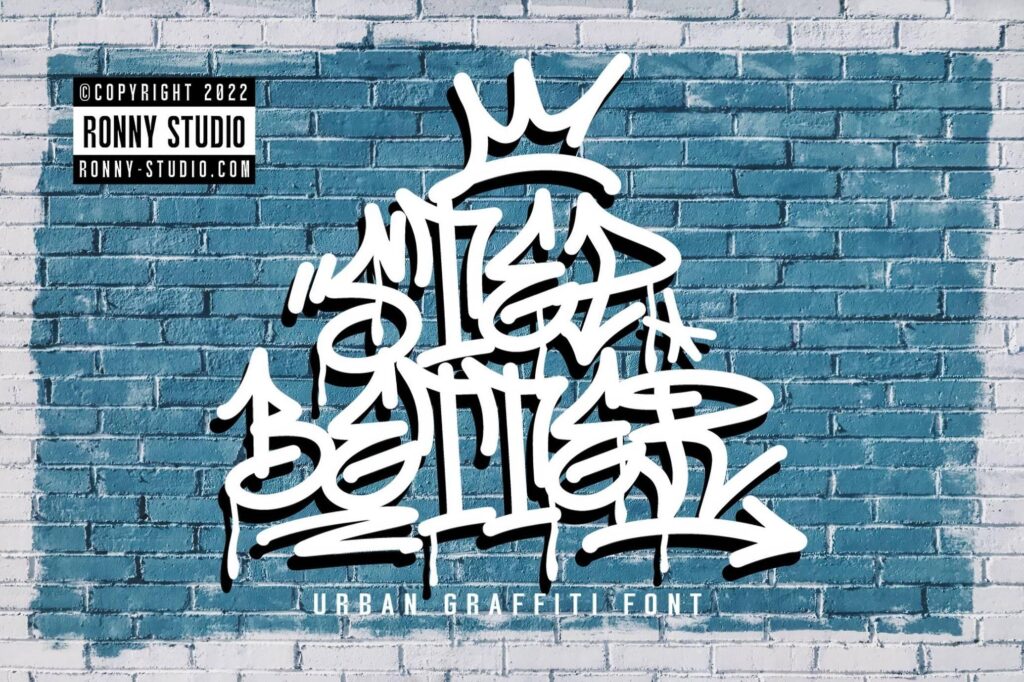
本記事では、用途がかなり限定されそうな超個性派の英語フリーフォントを紹介します。
使いやすい定番系フォントもうれしいですが「これどこで使うの?」と使う場所が限られそうな超個性派フォントも、無料ならアリ!ですよね。
それでは、早速みていきましょう。
クセがスゴい!用途が限定されるけどインパクト大!ユニークな英語フリーフォント【商用利用可能】
The Free Funky Fonts Bundle
Step Better — Urban Graffiti Tags Font
Lorida — Condensed Display
TGHEAD GEOMETRIC FONT
EVA POSHY FONT
TURKEYES — BOHEMIAN TYPE
WOLFGANG KRAUSS — MODERN FRAKTUR TYPE
Fleuron – Free Floral Display Font
Chubbo – Free Display Font
Hofmann – Free Experimental Typeface
Cibiru – Free Display Font
Gawker – Free Display Typeface
SURREAL PSYCHEDELIC TYPEFACE
▼商用利用可能なストリートの落書き風フォント「Kelsi – Free Graffiti Style Bubble Font」。ポップな雰囲気が気軽に演出できます。
Kelsi – Free Graffiti Style Bubble Font
▼商用利用可能なSVGフォント「LYON & CREST SVG FONT」。フォントのかすれ具合を強調したいなら、写真やイラストの上に重ねるのがオススメ。
LYON & CREST SVG FONT
▼商用利用可能なディスプレイフォント「KILLVINERS BLACKLETTER FONT」。クラシックな雰囲気もありつつ、今風のストリート感のある媒体にも対応できるタイムレスなフォントです。
KILLVINERS BLACKLETTER FONT
▼どこかレトロな雰囲気も感じさせるデザインフォントLEONE。
LEONE – FREE MODERN WESTERN FONT
▼大文字(縦長)と小文字(横長)を組み合わせるとスポーツチームのロゴっぽくなるフォントVINTAGE MONOGRAM FONT。
VINTAGE MONOGRAM FONT
▼アフリカの部族が使う文字や象形文字のようなJELANI DISPLAY FONT。
JELANI DISPLAY FONT
▼あえて混ぜて使いたい、5種類のフォントスタイルとボーナススタイルを収録したEXTRA CHEESE FONT COLLECTION。
EXTRA CHEESE FONT COLLECTION
▼斜めにカットしたようなズレを表現したフォントBISECT DISPLAY FONT。
BISECT DISPLAY FONT
▼中世ヨーロッパの物語のタイトルに使われていそうなAVIORTE BLACKLETTER FONT。
AVIORTE BLACKLETTER FONT
▼海外のアニメで使われていそうなかわいいフォントWONDER NIGHT DISPLAY FONT。
WONDER NIGHT DISPLAY FONT
▼スウォッシュが特徴的なLETTOWN HILLS DISPLAY FONT。ロゴデザインにも使えます。
LETTOWN HILLS DISPLAY FONT
▼パーツごとに別れていて、自由な色の組み合わせが楽しめるBETTER HOBBY DISPLAY FONT。
BETTER HOBBY DISPLAY FONT
▼二本のラインが入り組んだようなデザインフォントPIKOLO BLOCK ALT DISPLAY FONT。
PIKOLO BLOCK ALT DISPLAY FONT
▼O、R、Sが特にユニークなデザインフォントROUSSEAU ART DECO FONT。
ROUSSEAU ART DECO FONT
▼極太のウェイトでレトロ感漂うCAMAR VINTAGE FONT。意外に読みやすいフォントです。
CAMAR VINTAGE FONT
▼曲線とシャープな角のコントラストが印象的なMOLEN – FREE DISPLAY FONT。今っぽくもあり、どこかクラシックな雰囲気もあるフォントです。
MOLEN – FREE DISPLAY FONT
▼「Electroharmonix」は、まるでカタカナのように見える欧文フォント。用途はかなり限定されますが、持っておくとどこかで使う場面があるかもしれません。
▼「ColorTube Pro」はカラーOTFフォント。Adobe Photoshop CC 2018とAdobe Illustrator CC 2018または上位バージョンに対応しています。
▼あえて不ぞろいな感じを狙ったフォント「Shnobel」。イベント告知や子供向けの媒体など、楽しげな雰囲気で何かと重宝しそうです。
▼下からどんどん壊れて崩れ落ちているようなフォント「Breakaway」。ホラー映画に合いそうな書体です。
▼「Osaka」はクール系の媒体と相性が良さそうなフォント。長い文章には不向きなので、ロゴや見出しなどインパクトが必要な箇所に使うのがオススメです。
▼フォントの一部分が他よりはるかに太い「Bulky」。どことなくかわいらしくてレトロな印象が漂います。
▼「Manbow」は、まるで洋服のパターンを選ぶようにボディの柄が選べるフォント。特にドットは丸の大きさ別に数パターン用意されています。
Manbow
▼エレガントな雰囲気がおしゃれな「Cheque」。女性向けの媒体に重宝しそうな書体です。
▼文字の一部が斜線で構成されたフォント「Concre」。細めの文字ですがインパクトは大!UとVがいまいちわかりにくいので注意が必要です。
▼ヨーロッパの古い書物の見出しフォントのような「Rozalyn」。あらかじめ影のついたデザインになっています。
▼立体的でウェイトが細いデザインフォント「Folgore」。細部までこだわった、ポイントで効果的に使いたい書体です。
▼思いきり太めのウェイトがかわいい書体「Foo」。遠くからでも読みやすく、子供向けの媒体をはじめ、幅広い用途で使えそうなフォントです。
Foo
▼「Budmo」は内側のドットがかわいいデザインフォント。ヴィンテージ風の飾り素材とよくマッチします。
Budmo
▼ところどころ2ラインになったおしゃれなフォント「Anders」。ロゴやラベルなどを作るのに良さそうな書体です。
▼手書き風のかわいいフォント「Vinograd」は、多言語対応&イタリック体含めた4書体を収録しています。
▼「Krabuler」はちょっとレトロでかわいいイメージ。リガチャ(合字)のデザインも豊富で実用的なフォントです。
▼「Nuku Nuku」は太めのサンセリフフォント。スペルによっては読みにくい場合があるので、デザインする時は注意が必要です。
▼モータースポーツ系の媒体にぴったりの「Yukarimobile」。使う時は画像のように背景色と文字色のコントラストをはっきりさせると、カッコよくなります。
▼インパクト大の「Gang of Three」は、強い色でポスターなどに大きく使いたいフォントです。
Gang of Three
▼パックマンを連想させる「Crack Man」は、ゲーム風のかわいいフォント。影部分は別フォントになっており、影なしにもできます。
▼こちらもゲーム風の力強いフォント「Metal Lord」。近未来風のデザインとも相性がいい書体です。
▼「Stentiga」は小文字と大文字の組み合わせでデザインが楽しめるフォント。大文字がデザイン性強めになります。
▼「Vanilla Whale」は小文字の上下にラインが入った、西部劇に出てきそうなフォント。ヴィンテージ素材集と組み合わせて使うのもオススメです。
▼動物の足跡モチーフがかわいい「Ennobled Pet」。一字ずつ微妙に違う角度を向いていて、ベースラインもあえてふぞろいになっています。
▼大胆にデフォルメされた文字が特徴的な「Die Nasty」。こんなにデフォルメされていて読みづらそうなのに、一旦慣れてしまうとサクサク読めてしまう不思議なフォントです。
▼炎をモチーフにしたフォント「Heavy Heap」。炎のシルエットがわかり安いV・W・Yを多く含むロゴや見出しなどに特にオススメです。
▼いびつな形が落書き風で味のある「Chinese Rocks」。わざとベースラインをずらしたり、1字ずつ大きさを変えたりしても面白くなりそうです。
▼遊びゴコロいっぱいの「Stereofidelic」は、I・J・Tを多く含む文章でぜひ使いたいフォント。リガチャ(合字)もデザイン済みです。
▼横のラインが極端に太めの「Krait」。ボディの塗りだけのフォントとアウトラインフォントがあるので、色を自由に設定できます。
▼大文字の一部分が四角いドットになっているのがクールな「Term Free Font」。デザインフォントですが比較的文字が読みやすく、用途の広いフォントです。
▼文字それぞれに動きが感じられる「Xplor」。アクティブな印象なのでスポーツやキッズ向け媒体、イベント告知などに向いています。
▼もはや文字を読ませる気はないと思われる「Pattern Font」。フォントとしてよりパターンとして使う方が良さげです。
▼Font Bundles.netの「Presents – Pictorgram Font」は、プレゼントだけのピクトグラムフォントです。
Presents – Pictorgram Font